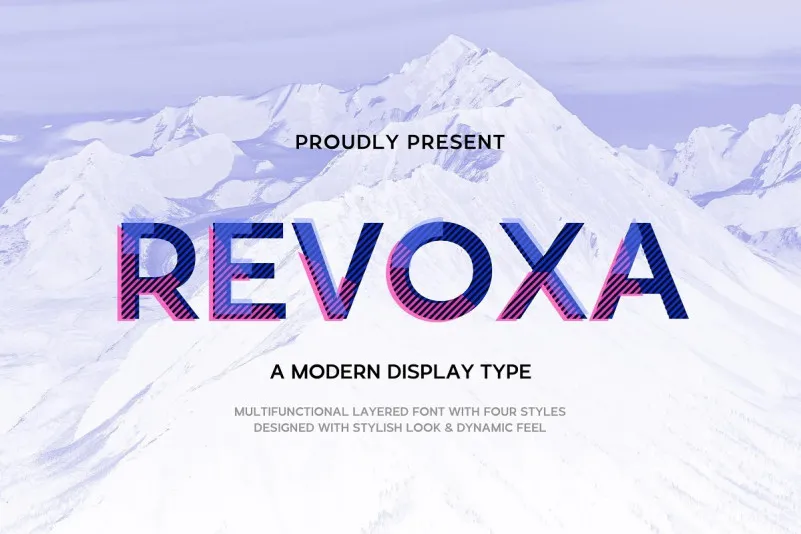
Descubra a versão ‘Revoxa Font’ dos 99designs no mundo do tipo digital. Esta elegante fonte de estilo de exibição vem inspirada num encantador retrato da rusticidade, uma fonte moderna e engraçadinha para o campo. Almarkha Type cuidadosamente projetou este design e compartilhou-o com a comunidade. As diferentes estilos foram criados para se “cobrir” uns aos outros, gerando um terceiro estilo alternativo incrível. Esta funcionalidade permite ajustar transparência e modos de mistura bem como diferentes configurações de cores, permitindo resultados variados. Revoxa é perfeita para designers que buscam combinar linhas claras com uma variedade de pesos em torno de um círculo. Perfeitamente adequada para usar como título em páginas de blog ou revistas, fazendo o texto fácil de ler e atraente sem deixar de ser moderno e inovadora. Essa fonte não só enriquece suas criações com uma identidade visual única, mas também oferece uma opção versátil para textos informativos e criativos em qualquer formato. Se você está procurando por algo que se destaque em sua próxima obra de arte gráfica ou projeto editorial, a ‘Revoxa Font’ pode ser exatamente o elemento complementar que faltava na sua coleção de tipos.